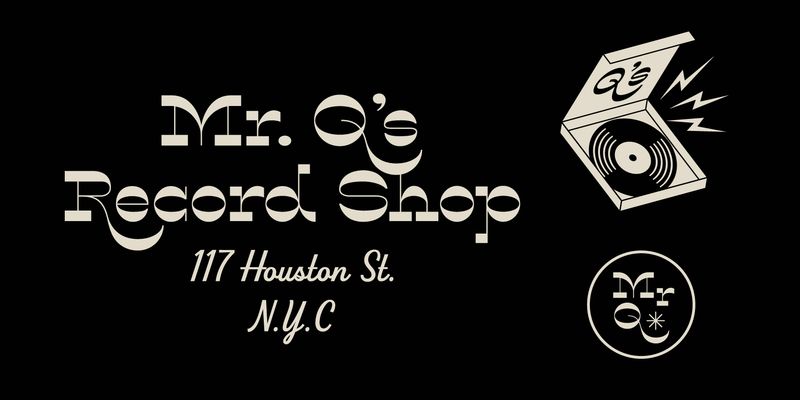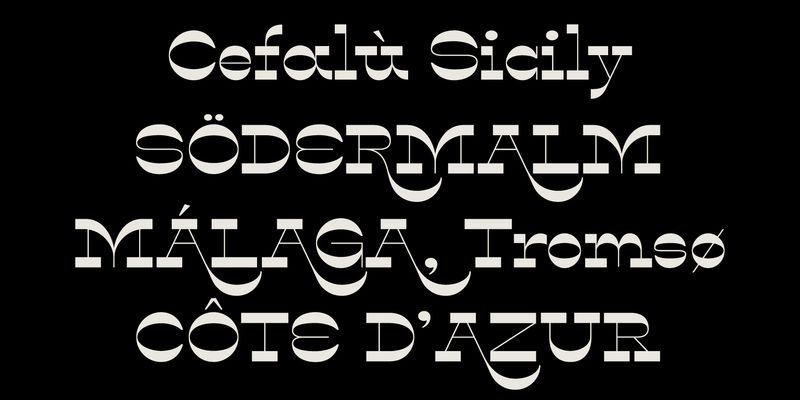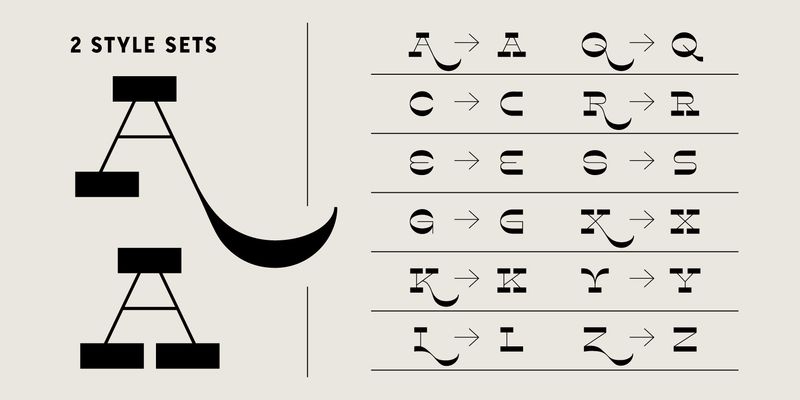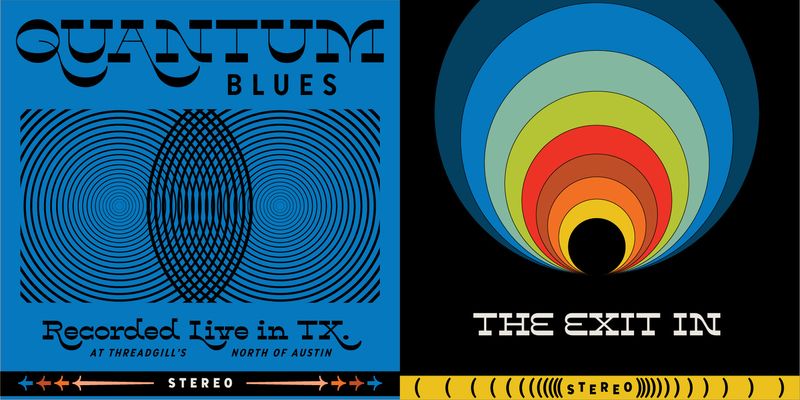
Lone Pine è un font serif a contrasto inverso con zazz e juuj al 110%. Ispirato alla Route 395 in California, questo font rende omaggio alle numerose città circostanti, come Lone Pine, CA alla base del monte Whitney. Questo font di visualizzazione ha un contrasto estremamente elevato e presenta grandi ornati per un effetto wow immediato. Attiva il set di stili OpenType 01 per un look fantascientifico più anni ‘70.